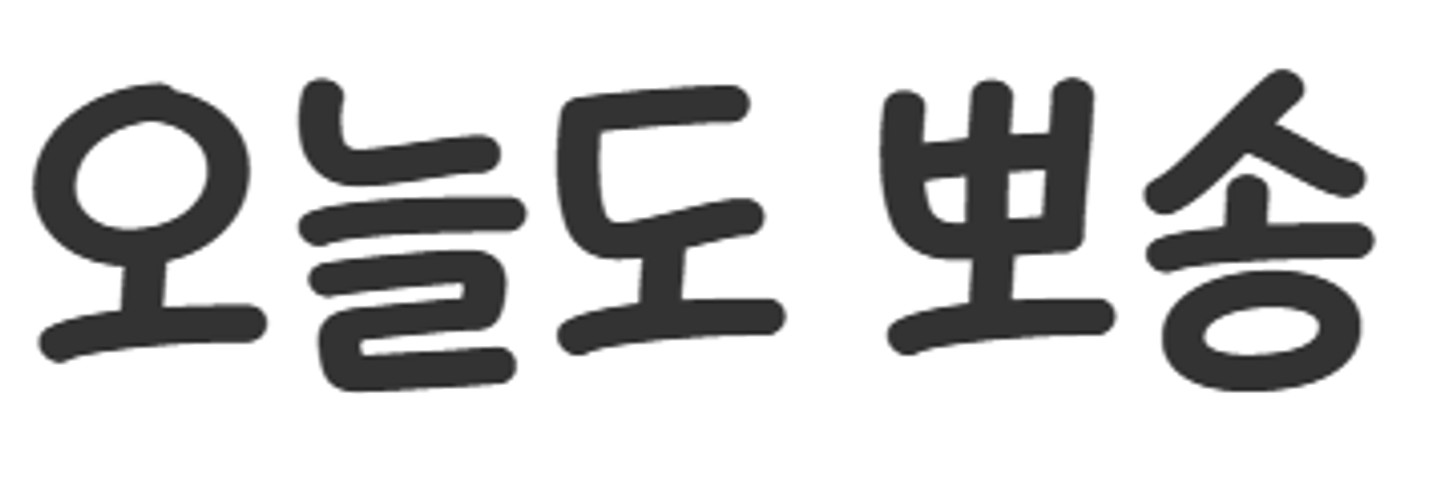
오늘도뽀송 부분 서체 궁금해요
AI로 생성돼서 폰트 식별이 어렵습니다.
올려주신 이미지는 실제 폰트가 아니라 AI로 생성된 텍스트로 보여 정확한 폰트 식별이 어렵습니다. (용,욕 일부 글자 깨짐 현상이 확인됩니다.) 따라서 동일한 폰트는 없지만, 비슷한 형태의 폰트로는 Dain 호빵손글씨 Heavy(유료)가 가장 유사합니다. https://www.sandollcloud.com/font/20338/Dain-Hobbang 추가로 무료 폰트에서는 온글잎 폰트,그리운 폰트 사이트에서 유사한 스타일을 찾으실 수 있습니다.